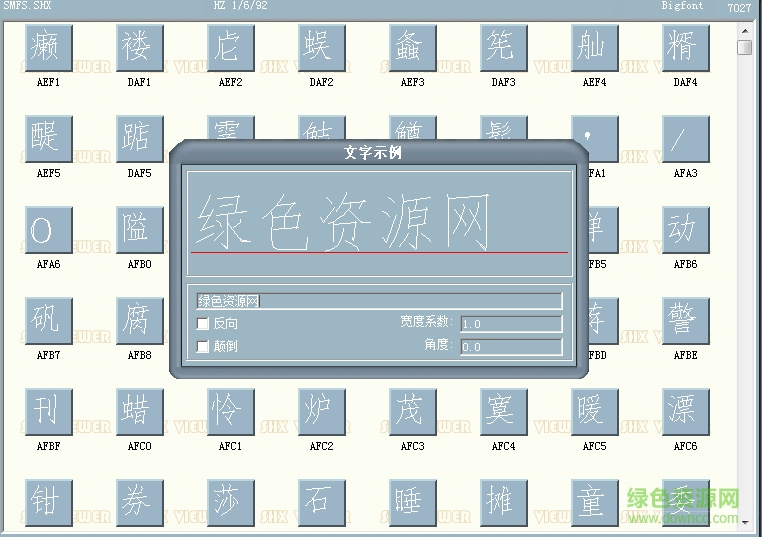
cad字體smfs.shx
smfs.shx字體是一款非常實(shí)用的cad字體,字體纖細(xì)美觀,非常的醒目,支持進(jìn)行中英文和阿拉伯?dāng)?shù)字的輸入,應(yīng)用非常的廣泛,有需要經(jīng)常用到各種cad字體的朋友,可以來綠色資源網(wǎng)下載這款字體使用!